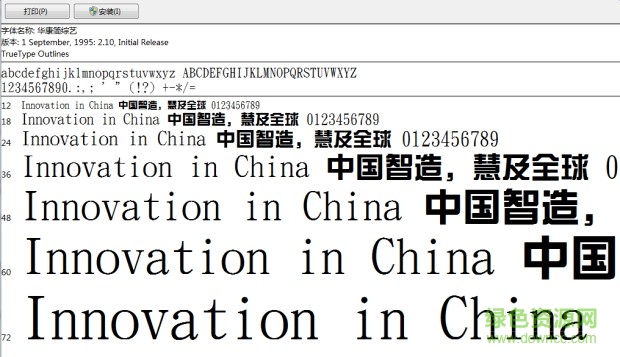
dfzongyi bd 80 win gb(華康簡綜藝)是一款粗壯雄峻的華康字體,字形渾厚醒目,筆畫飽滿晶瑩,看上去厚實(shí)有力,想要這款字體的朋友快來綠色資源網(wǎng)下載吧!
綜藝體是一種常用的美術(shù)字體,特點(diǎn)是筆劃更粗,盡量將空間充滿。同時為了美觀,對拐彎處的處理較為圓潤。方正、微軟等各大字庫都有開發(fā),常被用于廣告、報刊等的標(biāo)題。